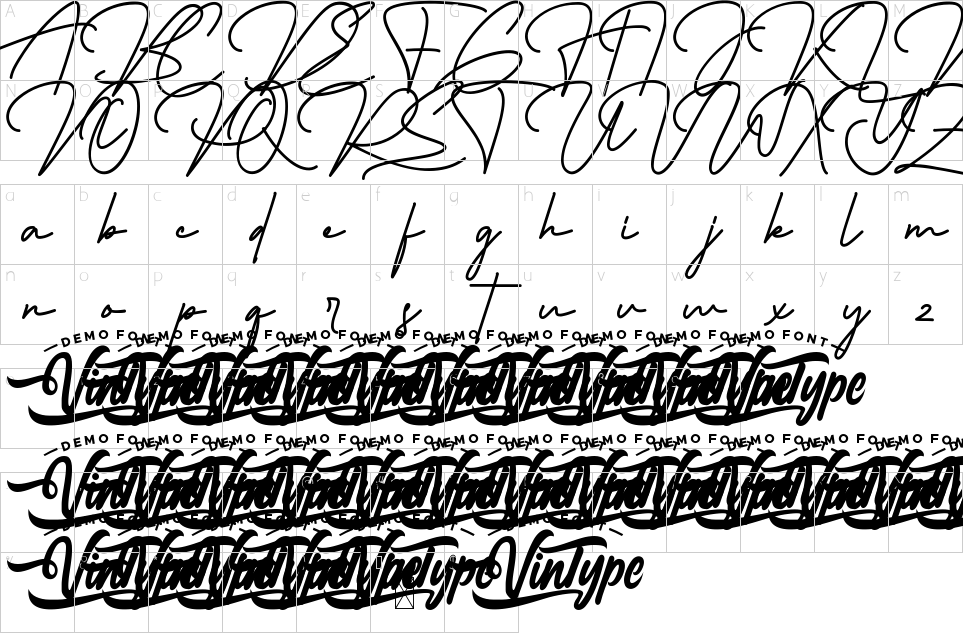
A fonte Masterline é uma escolha perfeita para designers gráficos que buscam uma fonte moderna e versátil. Desenvolvida por vintype, ela se destaca por sua elegância e facilidade de uso. Através do Masterline, você pode adicionar um toque de sofisticação a qualquer projeto, seja em design gráfico, layout web ou até mesmo em criação de mídias digitais. Esta fonte é ideal para designers que buscam uma opção de fonte neutra que se adapta a diversos estilos de design. Masterline foi descarregada 1.685 vezes, o que sugere que muitos designers já estão explorando suas possibilidades. Para aqueles que estão procurando por uma fonte de qualidade sem ter que desembolsar dinheiro, Masterline é uma excelente opção. Descubra o poder de Masterline e faça seu design soar ainda melhor.